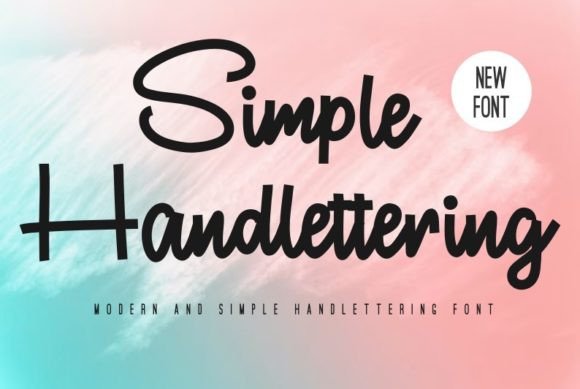
Simple Handlettering
Simple Handlettering์™€ ๊ฐ™์€ ๊ณ ํ’ˆ์งˆ ์ž์‚ฐ์„ ์ฐพ๊ณ  ์žˆ๋‹ค๋ฉด ์ด ํ”„๋ฆฌ๋ฏธ์—„ ํŒจํ‚ค์ง€๋Š” ์ฐฝ์˜์ ์ธ ํ”„๋กœ์ ํŠธ๋ฅผ ์œ„ํ•œ ํ™˜์ƒ์ ์ธ ์„ ํƒ์ž…๋‹ˆ๋‹ค.
POD(์ฃผ๋ฌธํ˜• ์ธ์‡„) ์ œํ’ˆ, ๊ฒฐํ˜ผ์‹ ์ดˆ๋Œ€์žฅ ๋˜๋Š” ์†Œ์…œ ๋ฏธ๋””์–ด ๊ทธ๋ž˜ํ”ฝ์„ ๋งŒ๋“ค ๋•Œ Simple Handlettering๋Š” ์ด์ƒ์ ์ธ ์„ ํƒ์ž…๋‹ˆ๋‹ค.